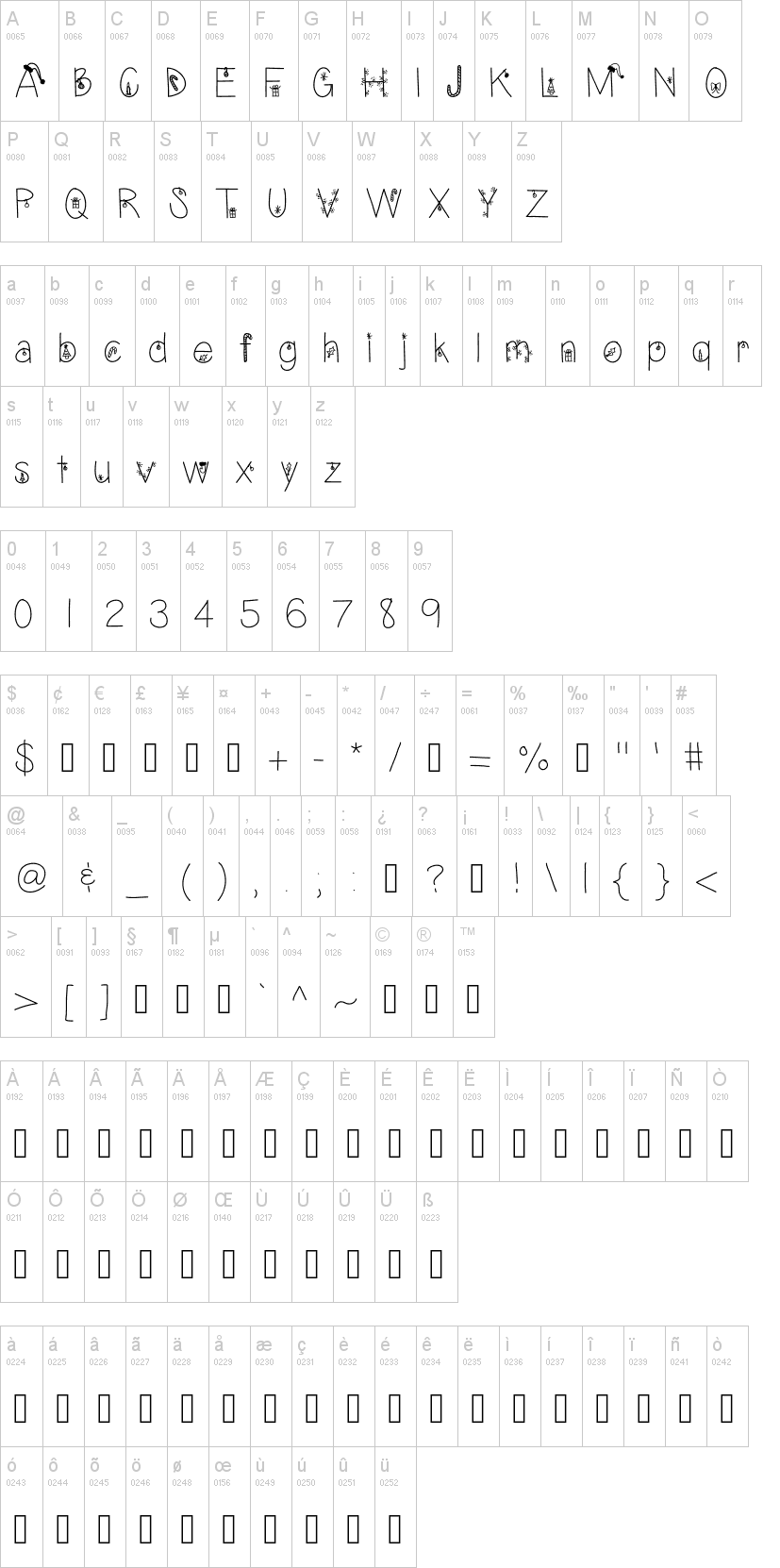
Christmas Eve 是一种节日风格的手写字体,非常适合用于圣诞节相关的设计项目,如节日贺卡、海报、广告等。这种字体具有温馨、轻松、有趣的感觉,它的字母和符号都带有圣诞节的元素,如雪花、圣诞树、礼物、鹿等。字母间距离相对较小,字母形态中也包含了一些手写风格的变化,使得该字体的整体视觉效果更为柔和。如果需要为圣诞节的设计项目增添节日气氛,那么选择Christmas Eve字体是一个不错的选择。内容介绍
Christmas Eve是一款非常不错的手写艺术字体,具有很好的视觉感,适合于文化类的宣传设计、商业类品牌的广告和产品包装设计以及个性化文字排版等较多场景。